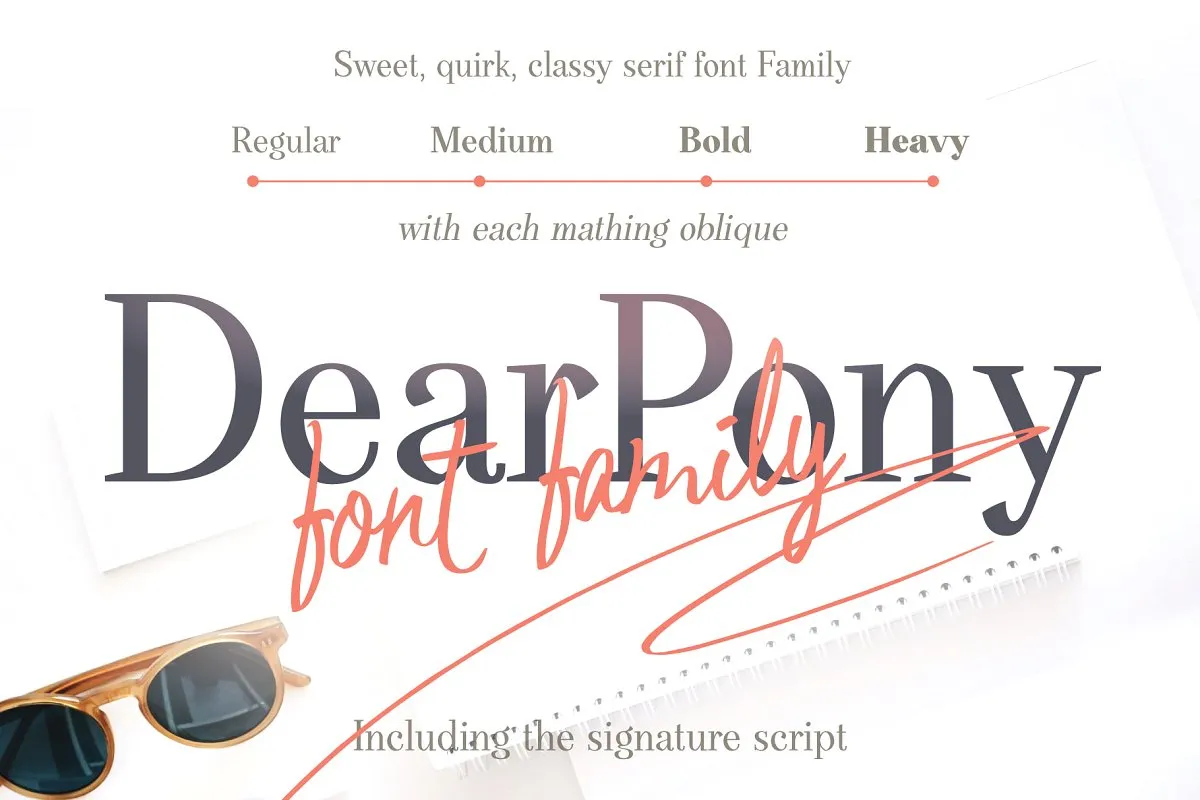
DearPony Serif Font Family – Download Grátis
Bem-vindos à M.0Type! Estamos muito felizes por vocês estar aqui hoje para explorar uma nova adição incrível a sua coleção de fonts: DearPony Serif Font Family. Introduzimos este elegante duo, que combina um conjunto serífiço com um estilo personalizado criado pelo talentoso Eko Bimantara. DearPony é mais do que simplesmente uma fonte; ele oferece uma experiência única e sofisticada, combinando uma serif caligráfica suave, quirk e elegante. Este encanto conjunto é perfeito para projetos criativos de todo tipo – desde identidades corporativas a trabalhos de design editorial. O conjunto serífiço vem com 240 gílitos, incluindo oito pesos: Regular, Médio, Bold e Obliquo. Cada peso tem seu obliquo correspondente perfeito para um uso fluido e harmonioso. Além disso, a fonte oferece suporte linguístico estándar latino multilingue. Mergulhe no mundo de DearPony Serif Font Family e descubra como ele pode transformar seus projetos. Experimente o estilo elegante e sofisticado deste conjunto serífiço com personalização única!